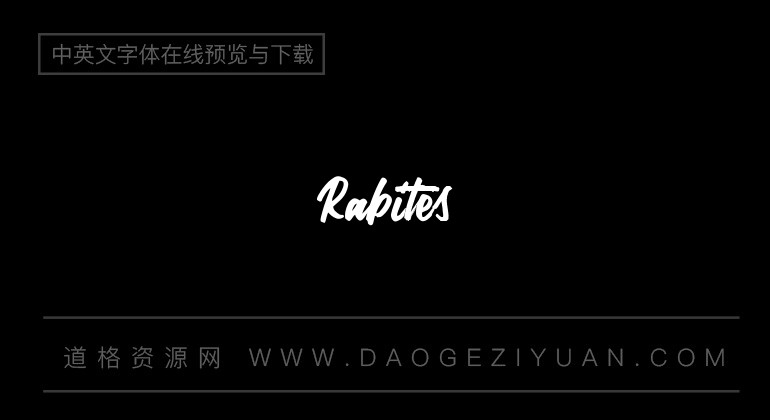
Rabites
Rabites 是一款简洁、清新、现代的英文字体,它由英国设计师 David Kerkhoff 创作,用于个性化的文本排版,特别适合用于标题、标签、标语等。它的字体特点是细节丰富,线条细腻,给人以柔和的感觉,但又不失现代感。Rabites 字体可以用于网页、印刷、设计、广告等多种场合,是一款非常不错的字体。
Rabites是一款非常不错的手写艺术字体,具有很好的视觉感,适合于文化类的宣传设计、商业类品牌的广告和产品包装设计以及个性化文字排版等较多场景。
Rabites字符映射图